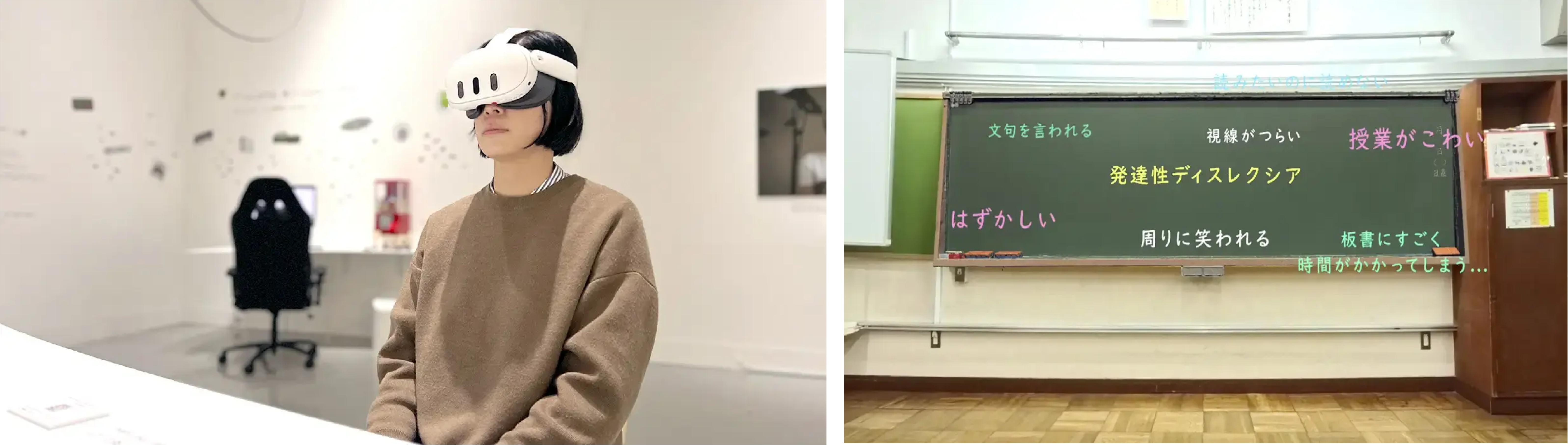
モリサワ 「ハッタツソンフェス2025」に協賛、VRコンテンツ『もしもディスレクシアの小学生なら』を展示【4/4・大阪】
株式会社モリサワ(以下、モリサワ)は、2025年4月4日(金)に開催される「ハッタツソンフェス2025」に協賛します。
ハッタツソンフェス2025は、「ひとりひとりが過ごしやすい社会」を目指して、感覚過敏や見えづらさの違いなど、多様な認知特性を持つ人々が共に創り上げるイベントです。「世界自閉症啓発デー」および「発達障害啓発週間」に合わせて開催され、ニューロダイバーシティ(神経多様性)の考え方を基盤に、インクルーシブデザインやアクセシビリティを重視した取り組みが紹介・発信されます。
この度、モリサワの展示ブースでは、ディスレクシア(※)への理解を深める機会として、資生堂クリエイティブ株式会社の提供によるVRコンテンツ『もしもディスレクシアの小学生なら』を展示します。このコンテンツは、来場者がディスレクシアに悩む小学生の状況をVRによって疑似体験できる内容で、ディスレクシアの生徒の授業中の困難さを再現しています。
また、より多くの人に伝わるように「文字のかたちがわかりやすい」「文章が読みやすい」「読み間違えにくい」をコンセプトに開発したモリサワのUD(ユニバーサルデザイン)フォントと、採用事例も合わせてご紹介します。
セッションプログラムでは、UDデジタル教科書体の開発者であり、UDの重要性を自著「奇跡のフォント」(時事通信社)などで発信している高田裕美が登壇して、UDフォントの活用法をわかりやすくお伝えします。詳細、聴講のお申し込みは、本イベント公式サイトにてご確認ください。
- (※)ディスレクシアとは
- 学習障害(LD)のひとつで、視覚・聴覚に異常がなく、知的に問題はない一方で、文字の読み書きに困難さのある状態。日本では約7〜8%の人が該当するとされていますが、その事実はあまり浸透しておらず、親、教師あるいは本人でさえ気づいていないことがあります。
セッション情報
タイトル:必要とする人に届けるUDフォントの活用法とは?
概 要:教科書・教材のために開発された丸ゴシック体で、「UDデジタル教科書体」と同様に子どもたちの学習を支援する「UD学参丸ゴシック」が2024年8月にリリースされました。UDフォントにも、明朝・ゴシック・丸ゴシック・教科書体と色々な種類がありますが、その使い分けは?/UDフォントを使いさえすれば読みやすくなるの?/どうしたらUDフォントを使えるの?などユーザーからの疑問に「UDフォント」の開発者が答えます。